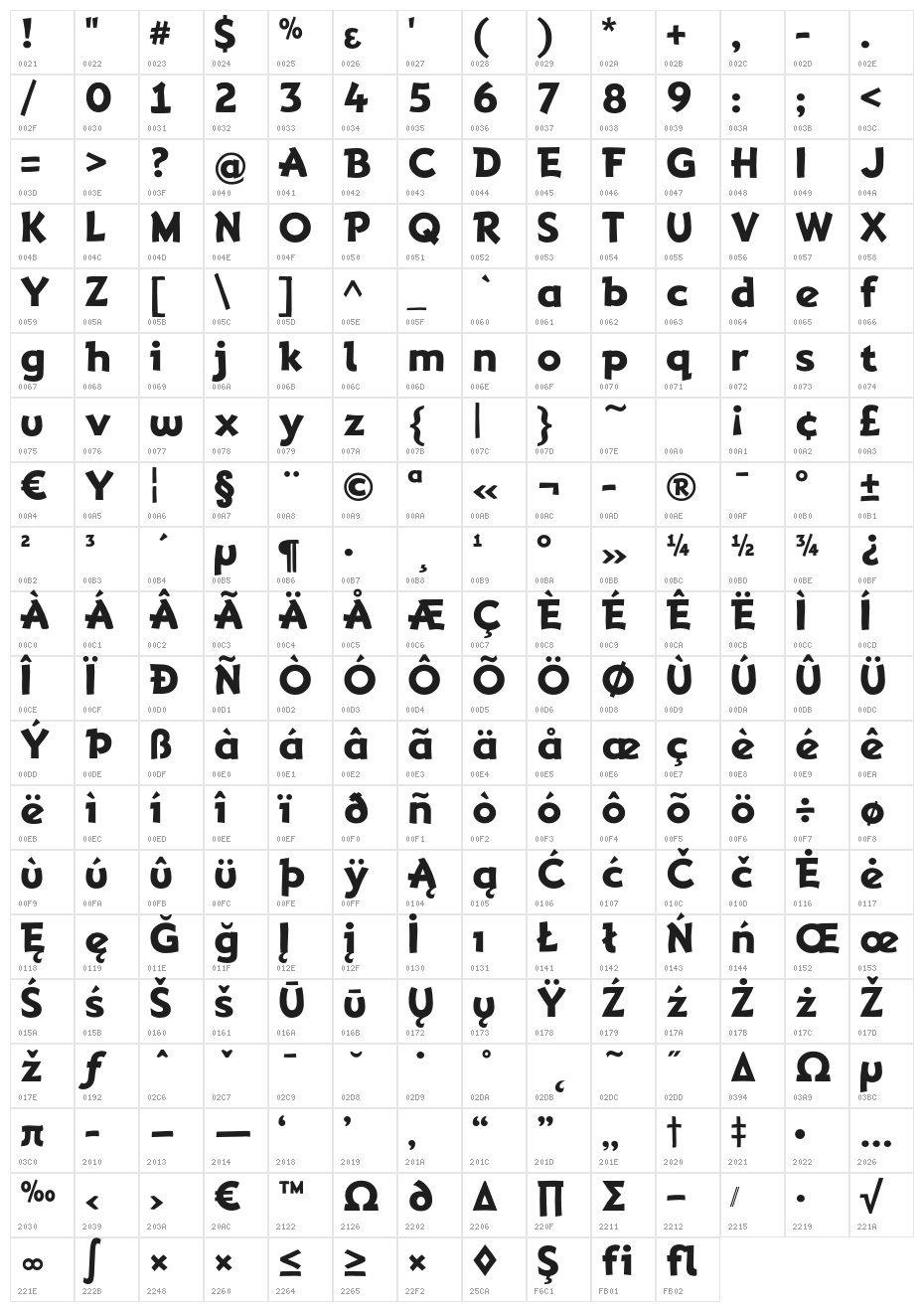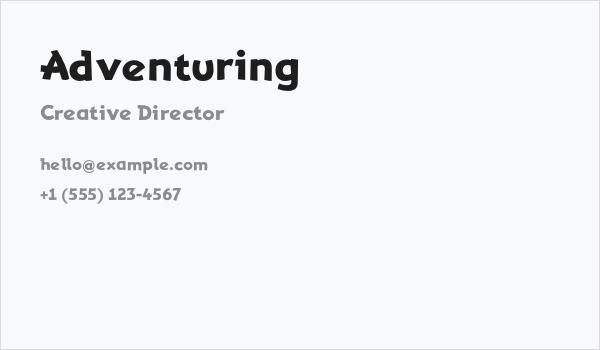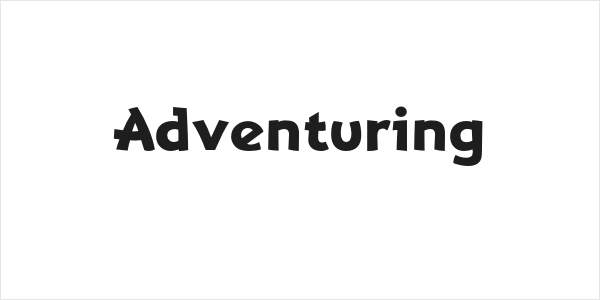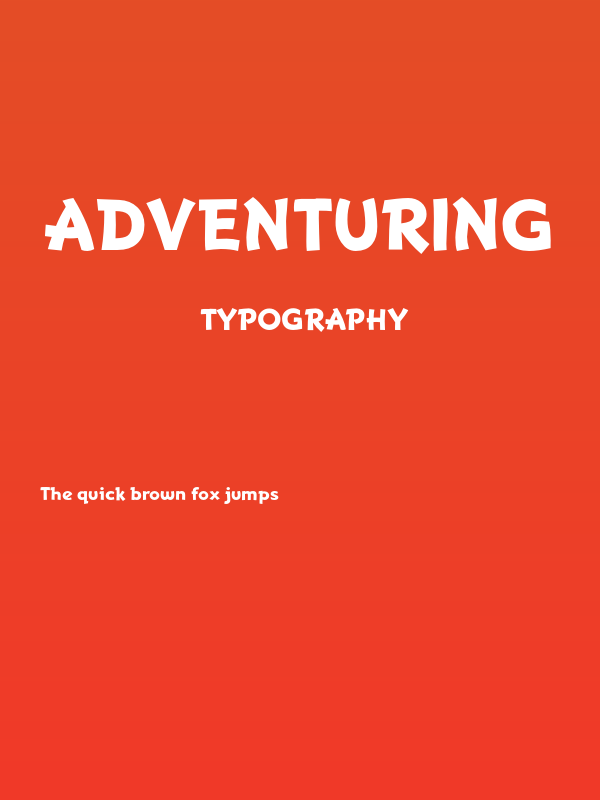
Adventuring Font
| 整体风格 | Playful, Adventurous |
| 推荐项目 | Ideal for children's books, adventure-themed posters, playful branding, and video game graphics. |